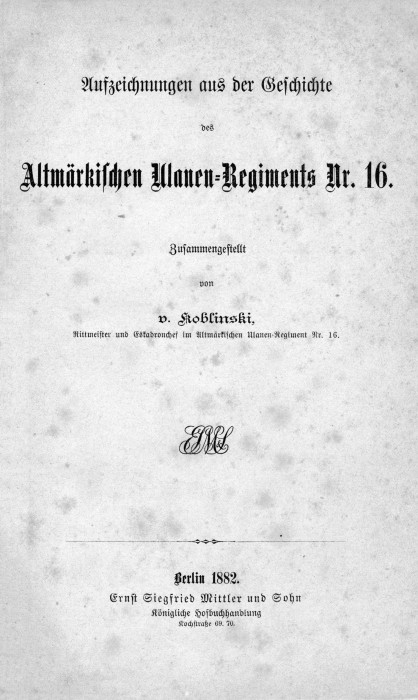
Könnt Ihr mir bitte helfen? Welche Schriftart kommt dem am nächsten?
Welche der mindestens 3 (wenn man vom Verlags-Logo absieht) ?
"Aufzeichnungen aus der Geschichte" und "Zusammengestellt" ist eine halbfette Normalfraktur, die teils mit unterschiedlichen Namen, teils auch nur mit einer Nummer bei vielen Schriftgießern im Programm war.
"von", "Rittmeister..." und die Verlagsangabe unten sind die normale Variante hiervon,
"Altmärkischen Ulanen..." und "Berlin 1882." dürften eine Schmale halbfette Gotisch sein.
von Koblinski hab ich auf die Schnelle nicht gefunden, gut Möglich, das auch die in der Liste ist,